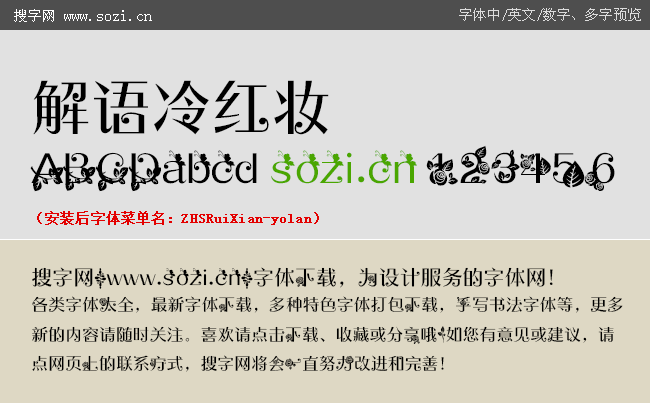
解語冷紅妝字體
解語冷紅妝字體是一款是由搜字網(wǎng)提供中文字體下載,字體名字很有古風意境,中文字體部分設(shè)計很有特色。英文字體和數(shù)字部分更配上玫瑰,蝴蝶,葉子等圖案。是一款用于非主流設(shè)計方面的字體,可用于廣告設(shè)計字體、網(wǎng)頁設(shè)計字體、包裝設(shè)計字體、 屏幕顯示字體等。歡迎下載!